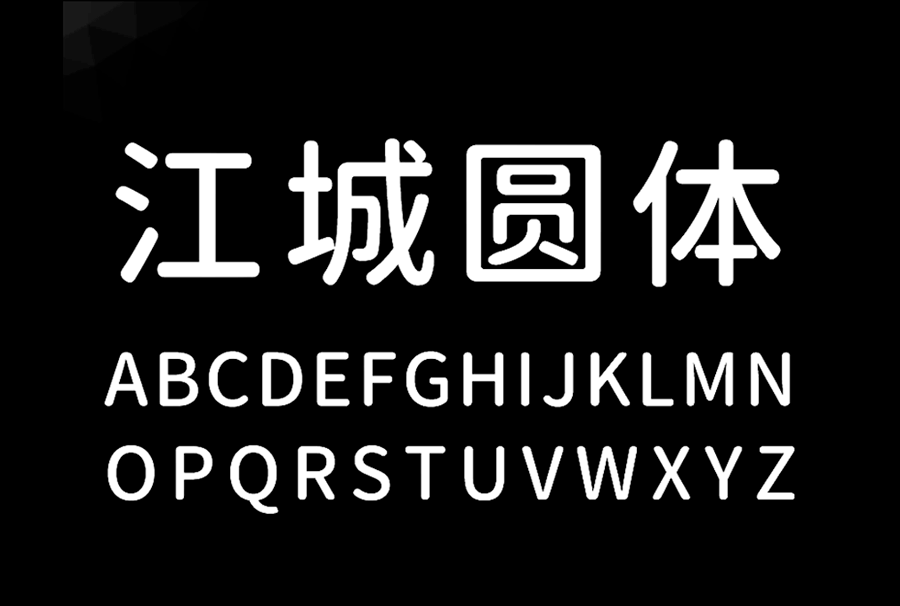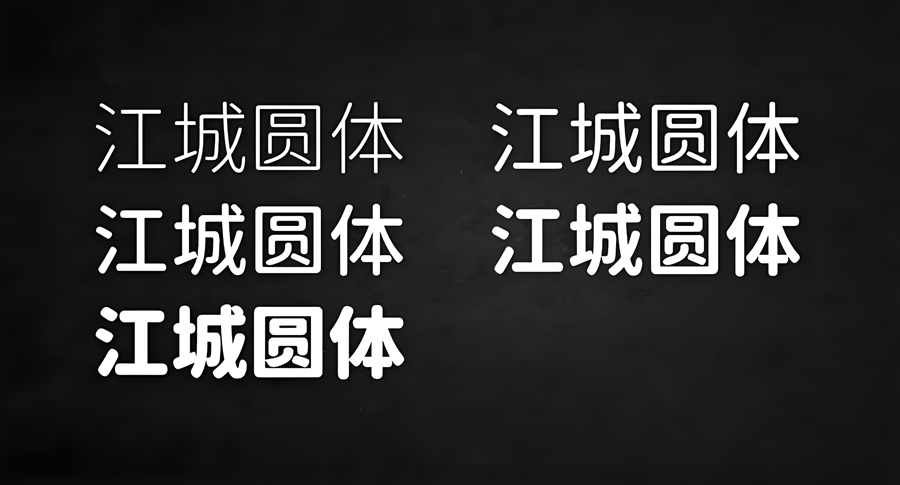
江城圆体是由设计师刘鹏(@设裂星辰)基于台湾地区的源泉圆体改造的一款免费商用简体中文字体,目的是为了解决大陆设计师使用台湾圆体时常见的缺字问题。
源泉圆体本身是基于思源黑体改造的一款圆体字体,江城圆体在此基础上进一步优化。将黑体中的衬脚全部去除,内部拐角处进行圆润平滑处理,尤其是手机或网页阅读时的显示效果。不仅使字体看起来更加圆润饱满,而且清晰易读。
江城圆体提供 5 种字重(300W-700W),覆盖 GB2312 标准汉字,基本无缺字,可以满足简体中文的各种排版需求,比如品牌设计、宣传物料、数字界面或者新媒体正文等场景。